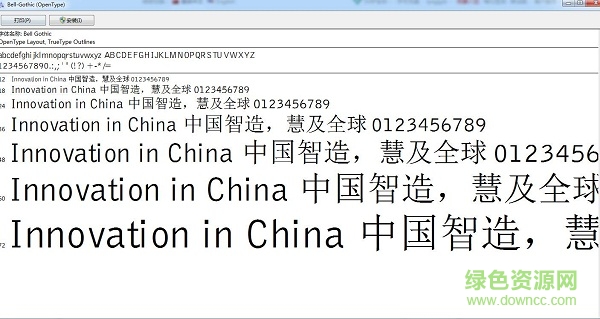
bell gothic字體是一款無襯線字體,細(xì)節(jié)豐富,線條變化自然又不失規(guī)矩,實(shí)用性較強(qiáng),適合用于網(wǎng)頁設(shè)計(jì)、Word排版、電子圖書等方面,喜歡的朋友快來下載吧!
其均勻的筆劃寬度和平滑的筆劃弧度表現(xiàn)出一種穩(wěn)定的、充滿機(jī)器意味的無時(shí)間性及共時(shí)性特征,造型規(guī)整,富于力度,有較強(qiáng)的視覺沖擊力!